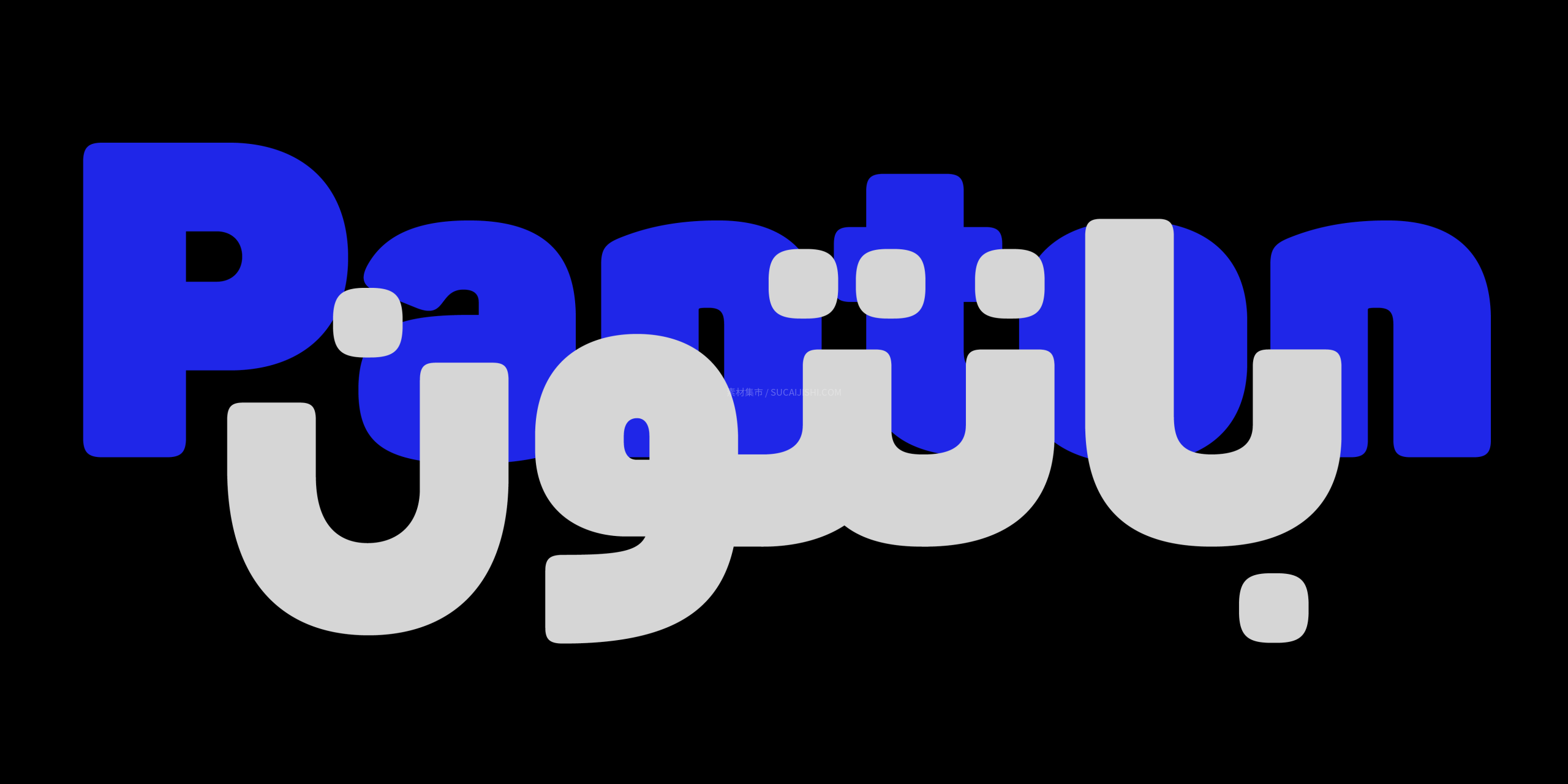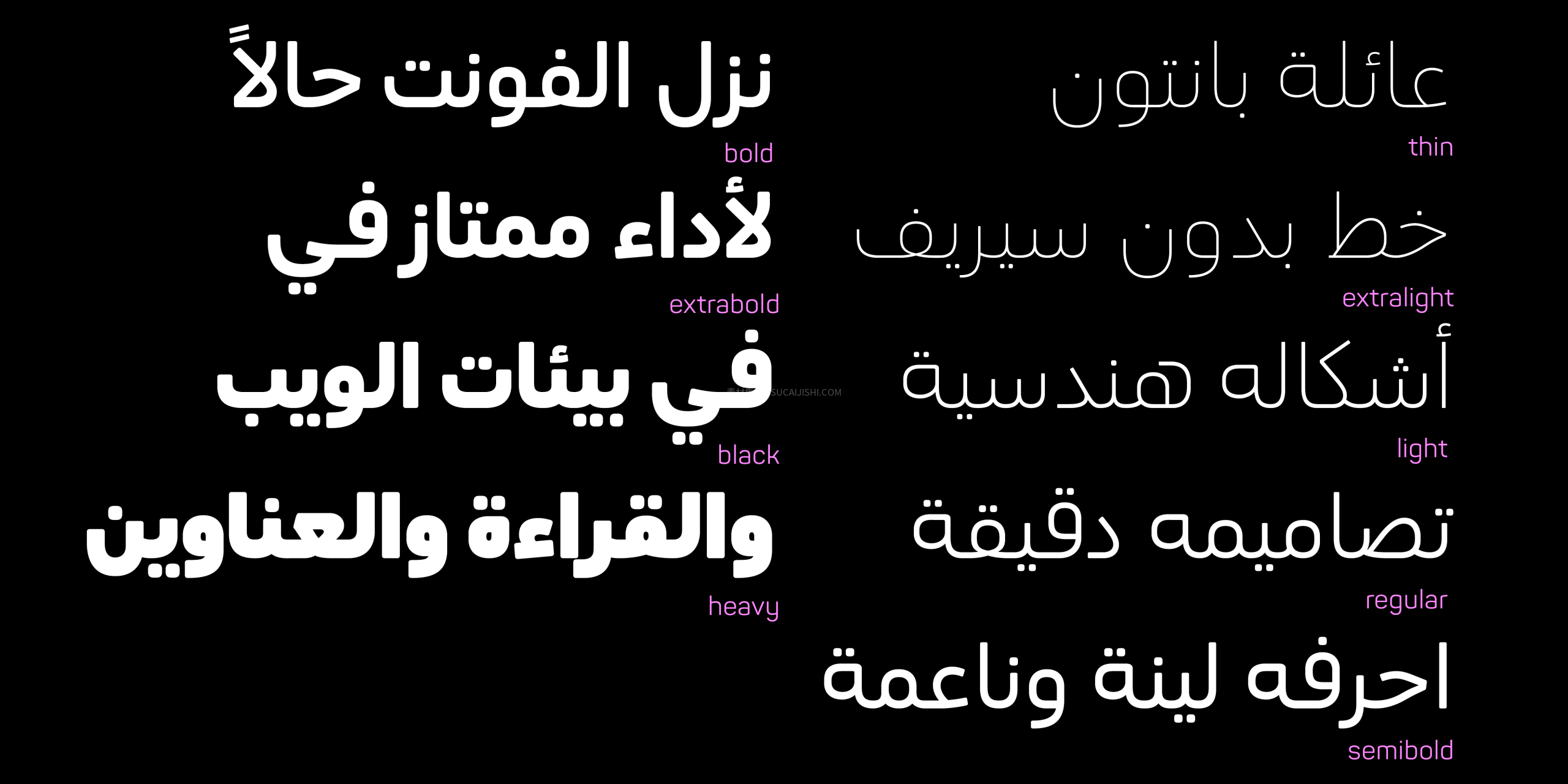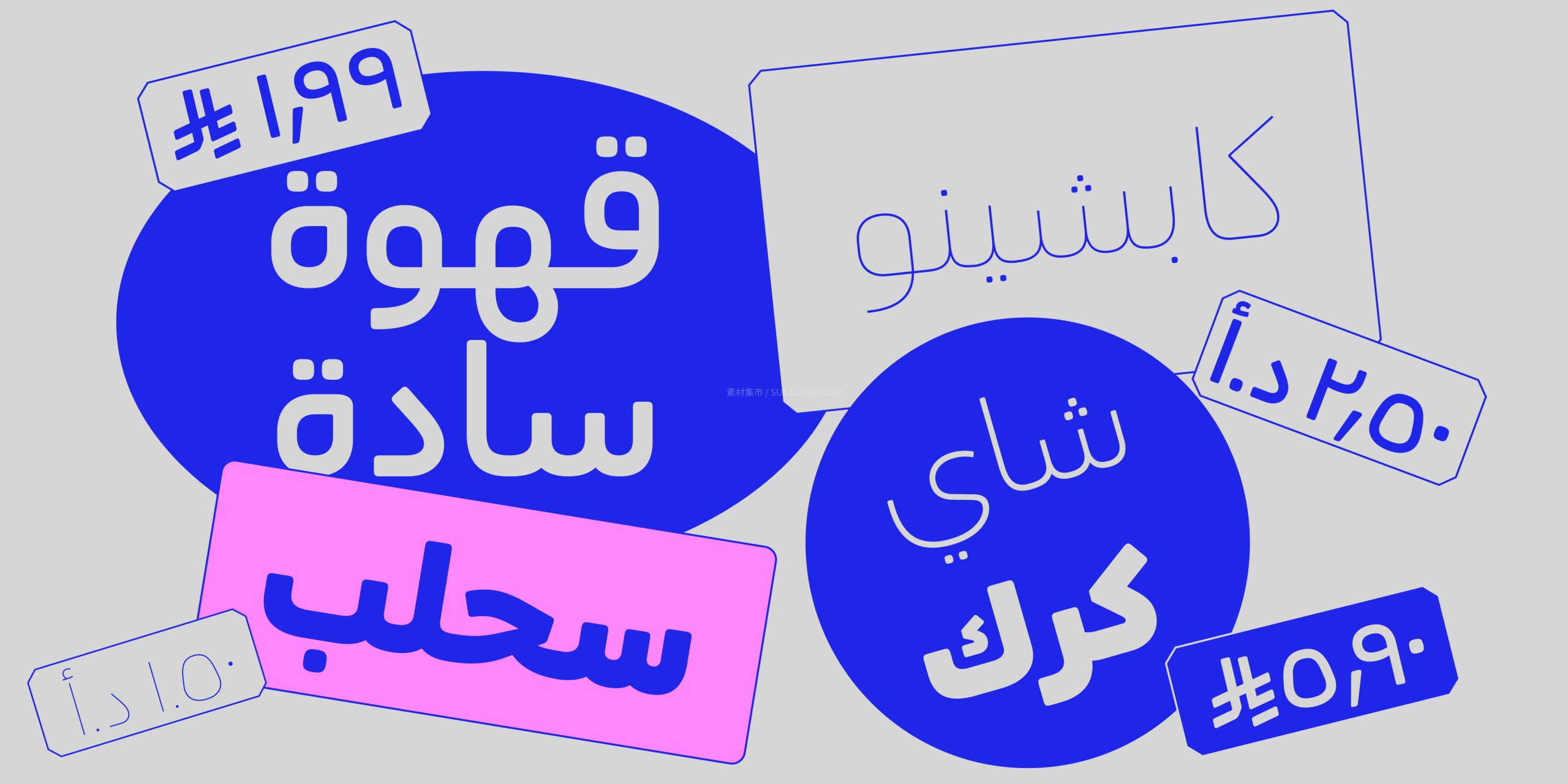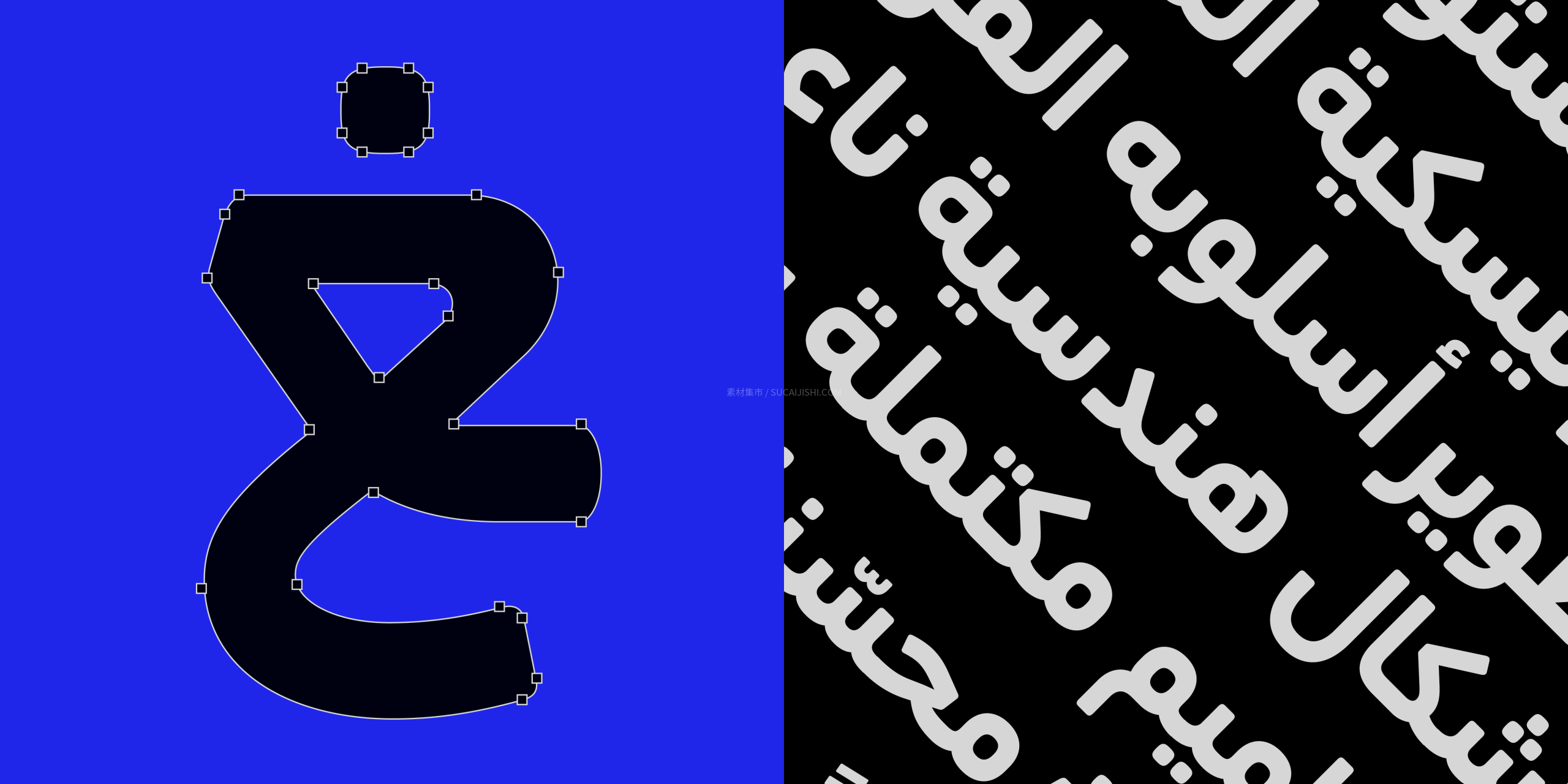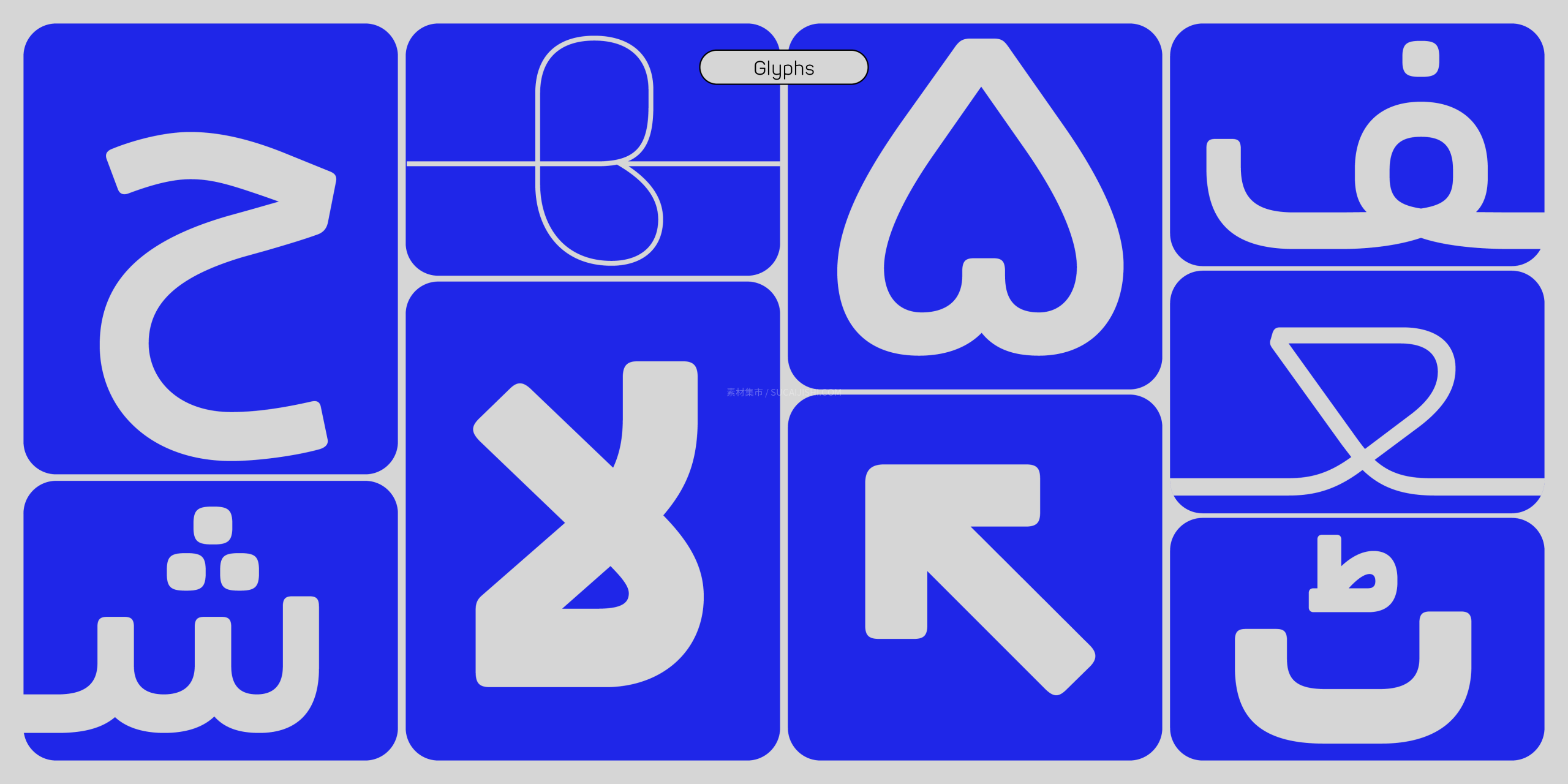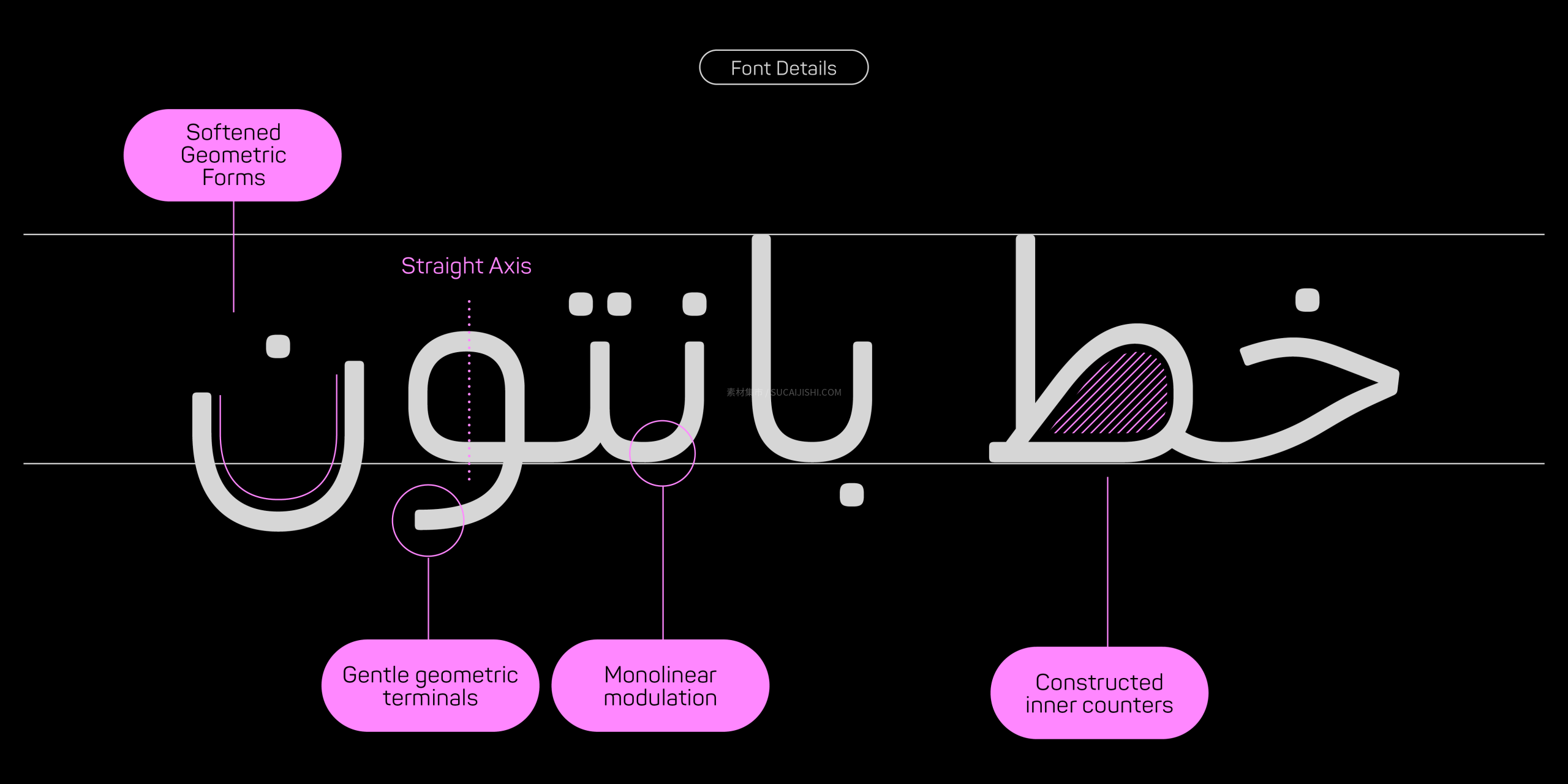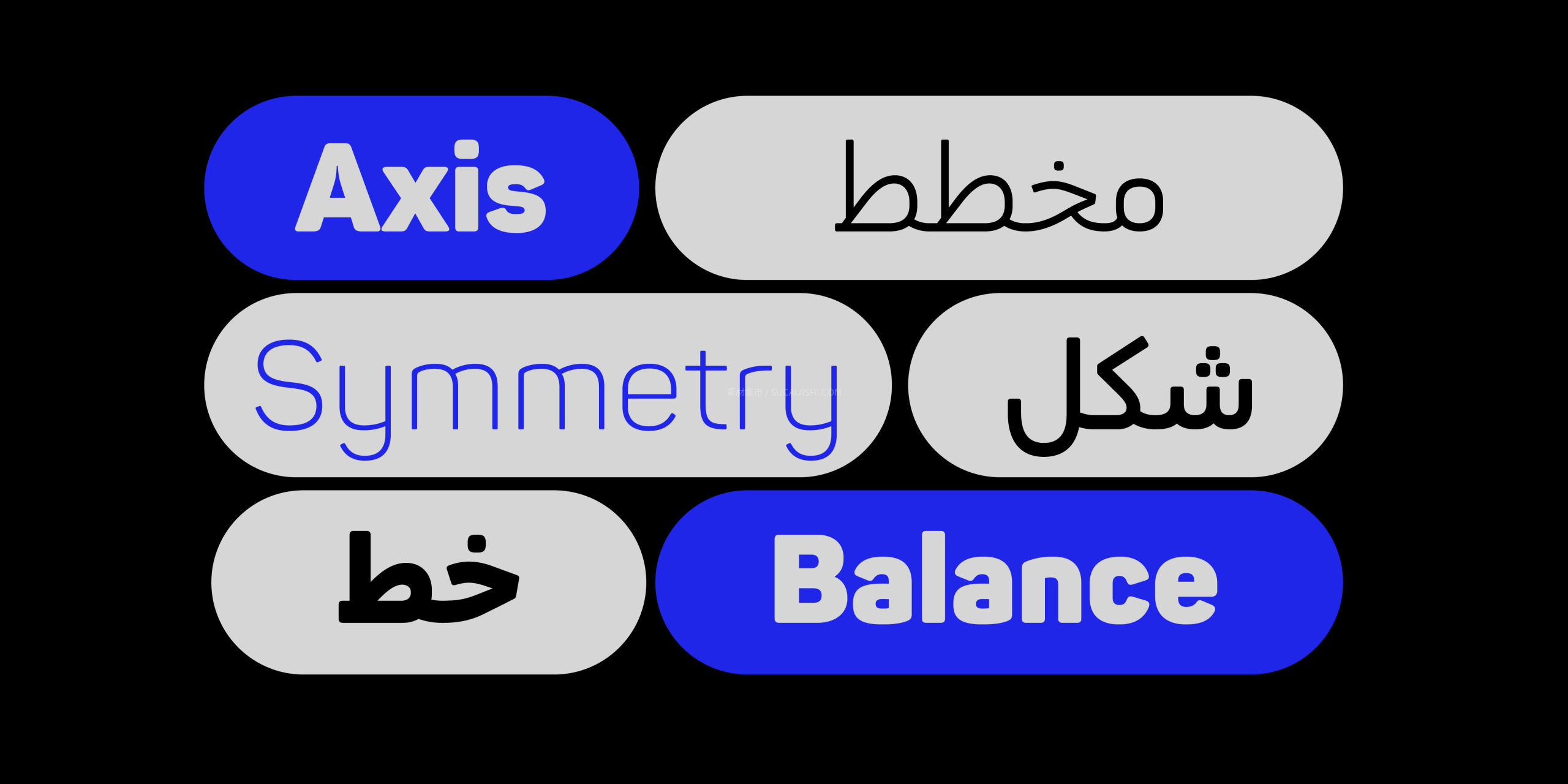
Panton Arabic 阿拉伯可变字体字体
Panton Arabic 是一款专为全平台高标准创意设计打造的现代几何无衬线字体。它拥有柔和的几何结构和现代阿拉伯语字符,在富有表现力的标题与高易读性的正文之间切换自如。字体家族包含 9 种静态字重与 1 种灵活的可变字体(Variable Font),支持高级 OpenType 特性与强大的跨脚本多语言兼容性。无论是品牌视觉系统、UI/UX 界面设计、现代数字出版还是响应式网页,Panton Arabic 都能为你的排版注入精致且面向未来的视觉张力。